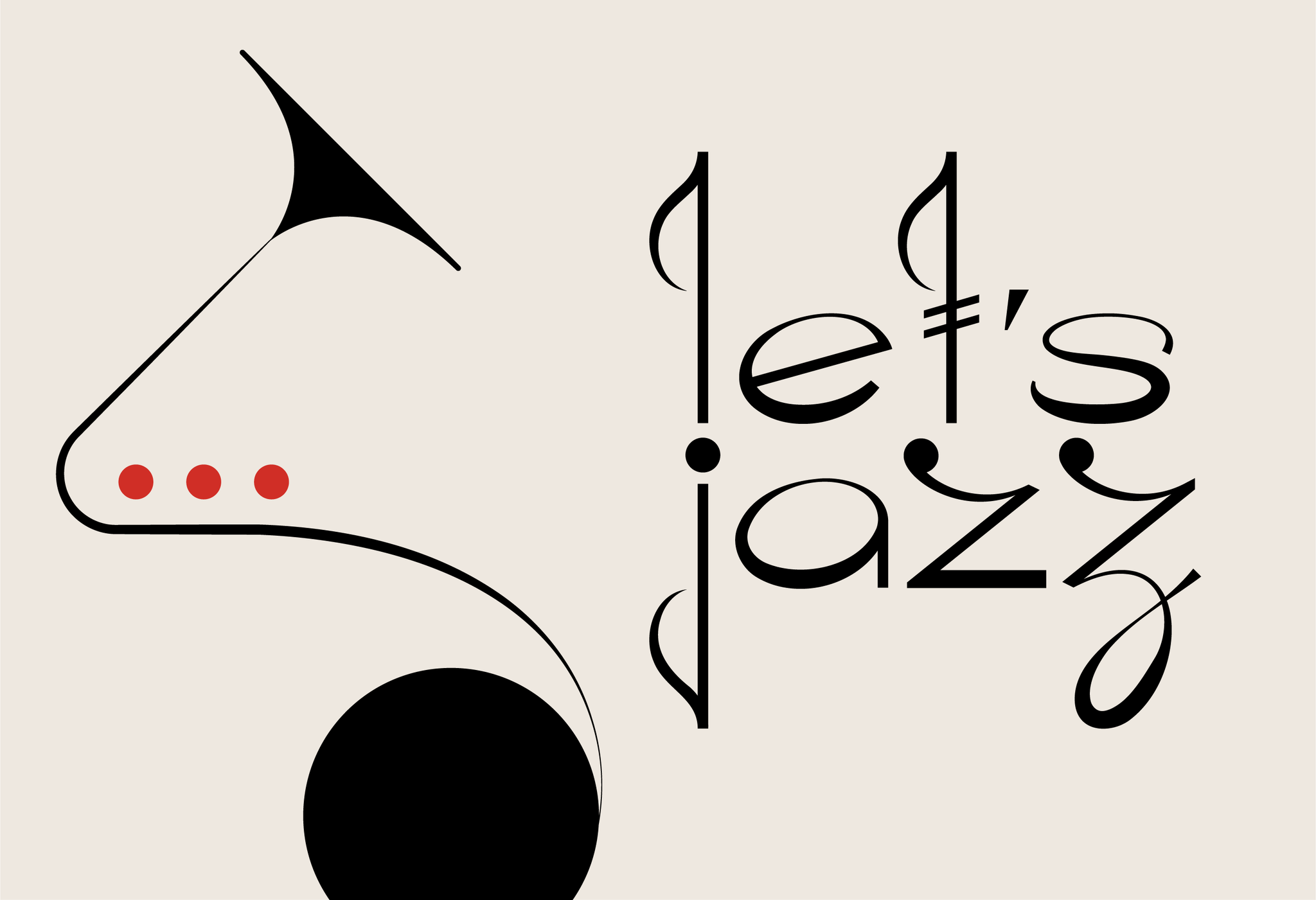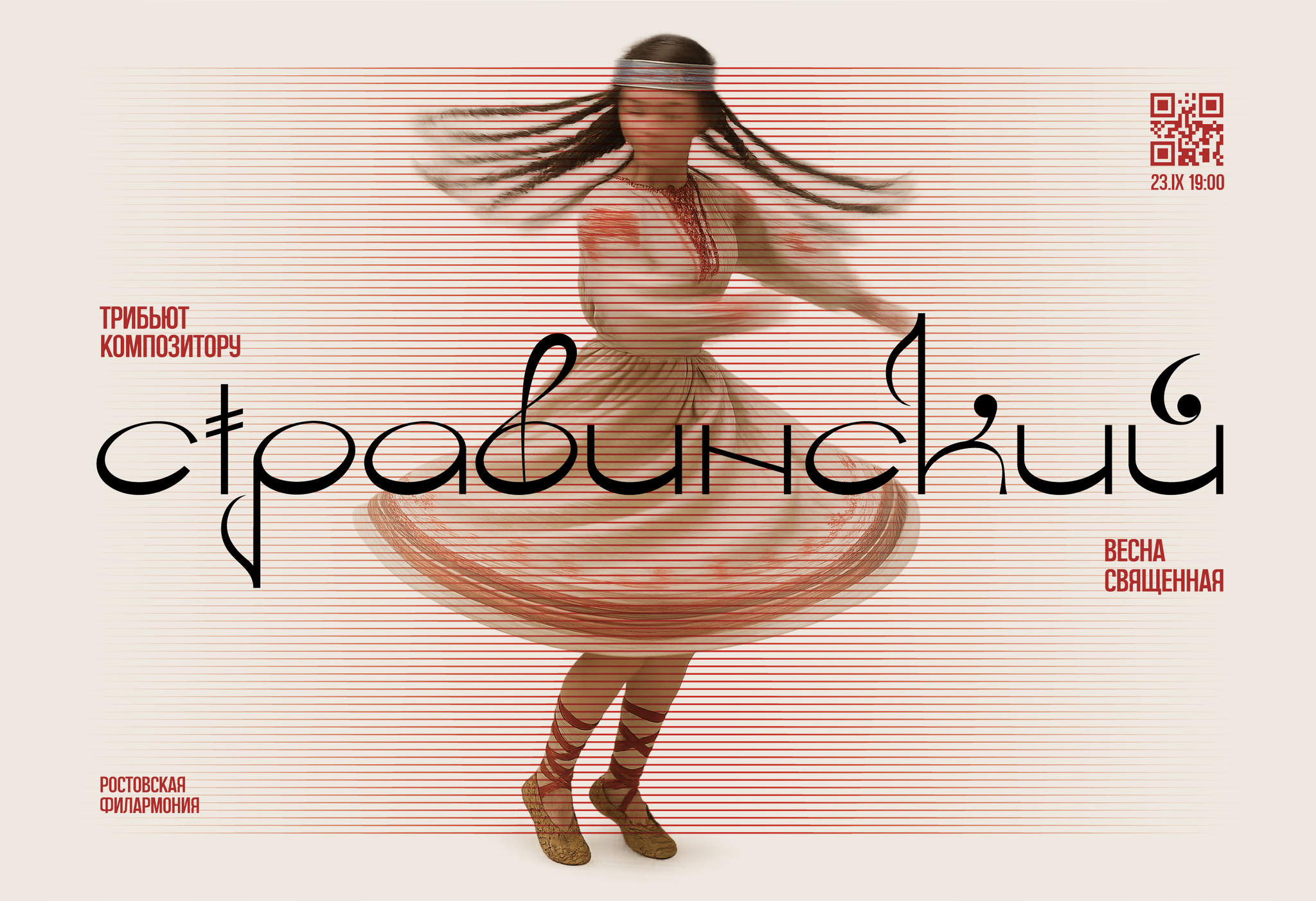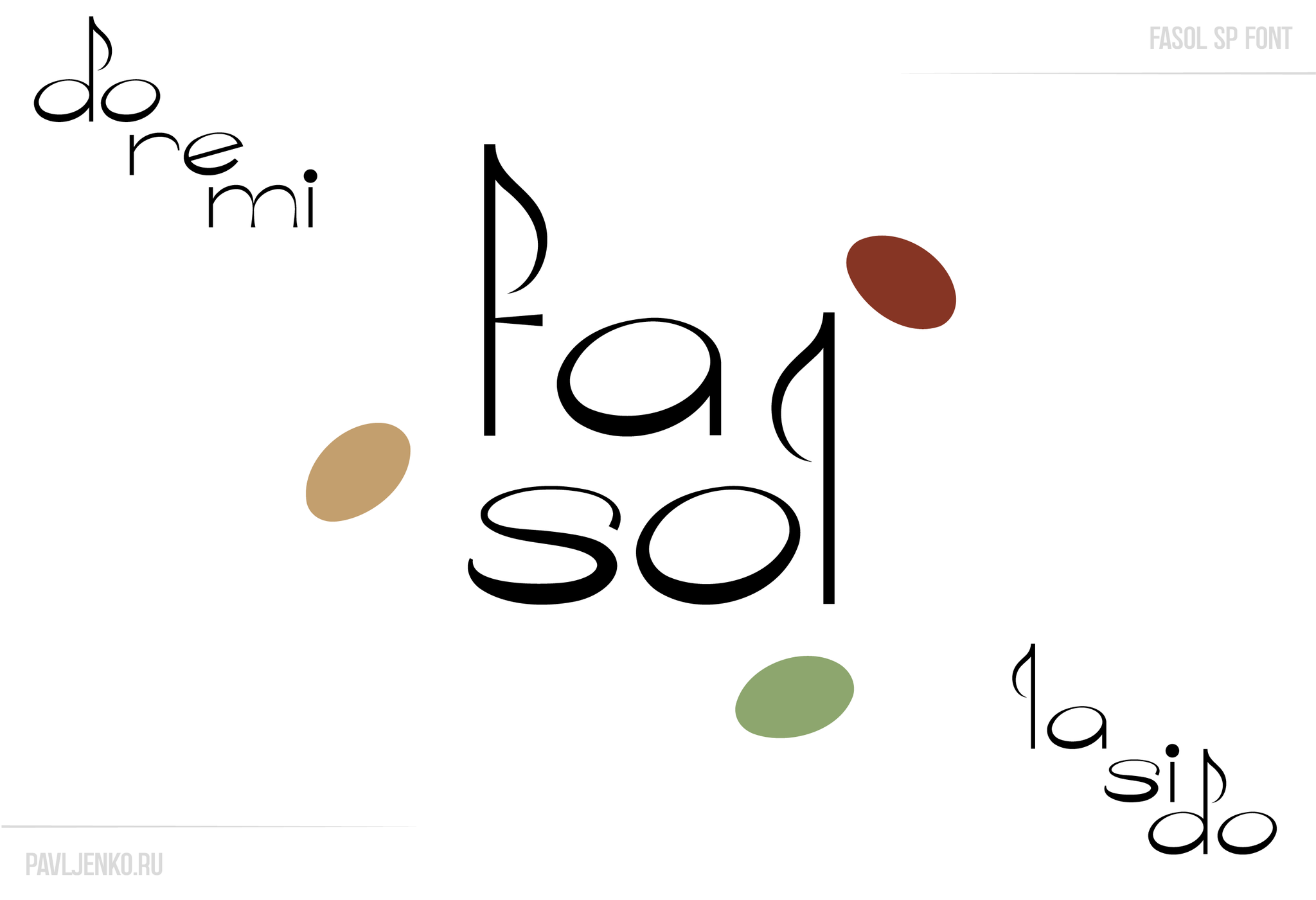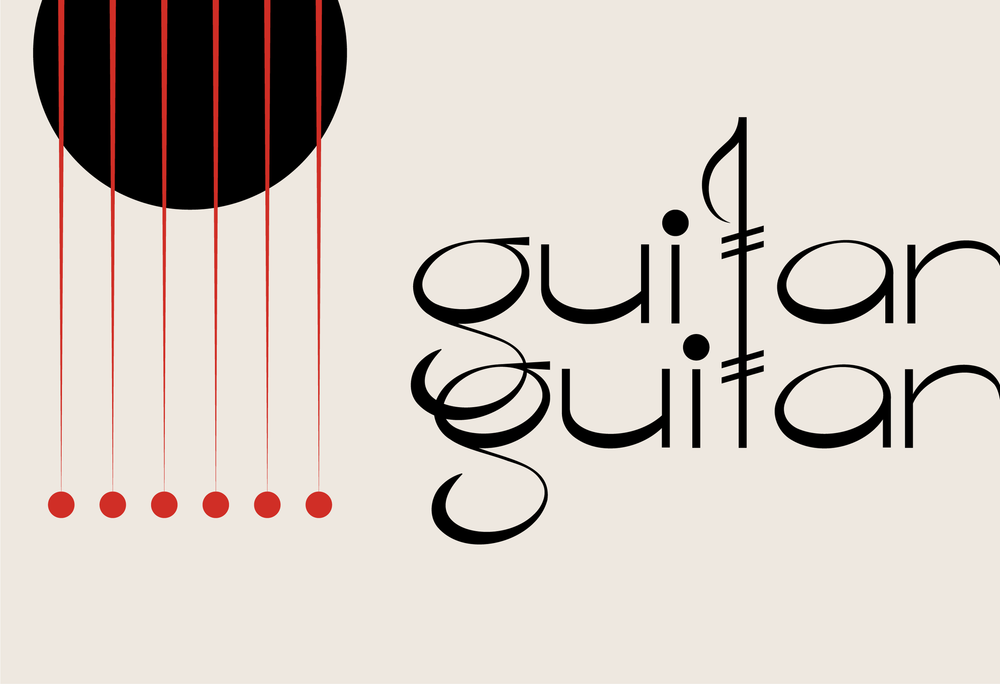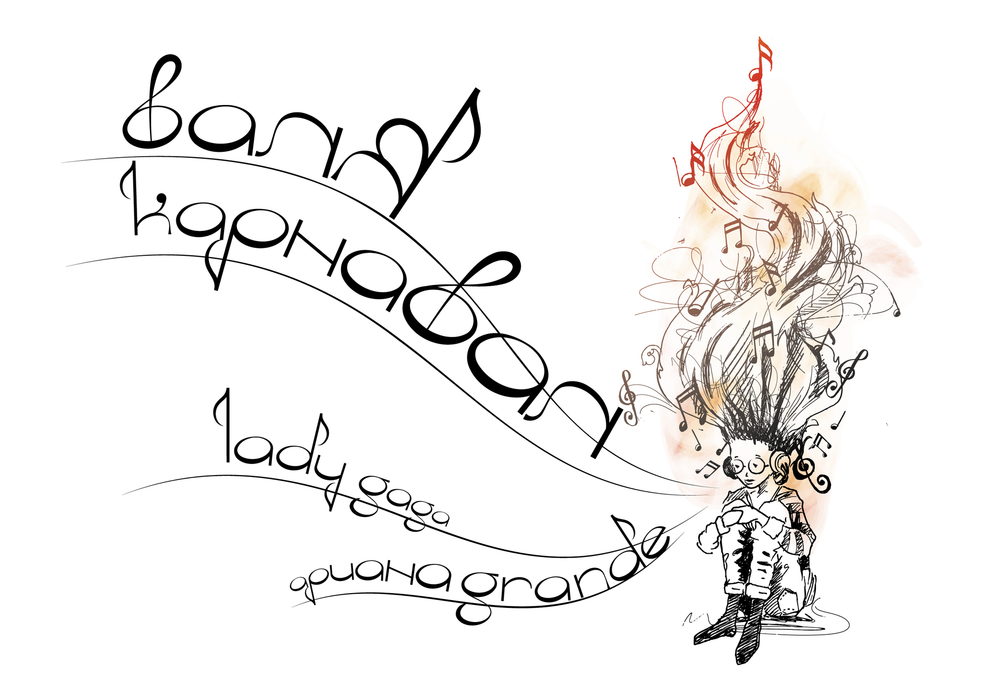
Шрифт Фасоль
Fasol — экспериментальный декоративный шрифт, в котором сходятся каллиграфия, письменность древних культур и музыкальная нотация. Скрипичный ключ, повторяющийся ритм штрихов и отдельные знаки, похожие на ноты, превращают строку в подобие партитуры, а петли и завитки добавляют ей движение. Чаще всего он попадает на обложки альбомов, в логотипы и постеры джазовой, фолковой и авангардной сцены. В комплекте — полная версия STAR и лицензия.